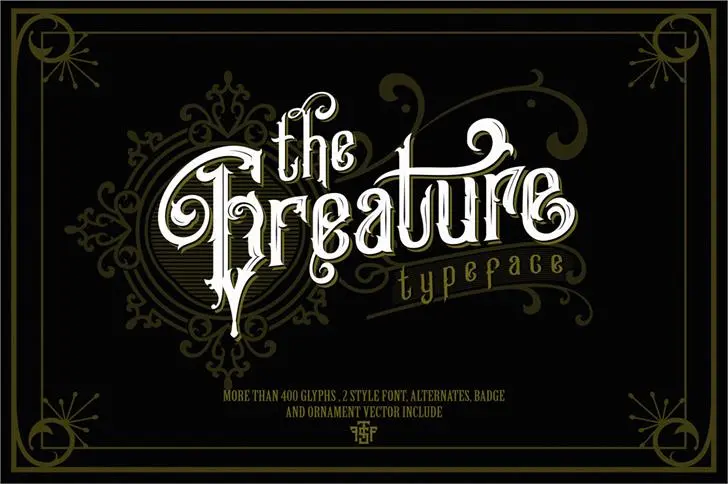
Introduzimos a Greature Font! Desenhada pelo Hamilton, esta fonte apresenta mais de 400 glíptons em duas estilos distintos: Regular e Shine, incluindo conjuntos estilísticos, ligaturas, alternativas contextualizadas e extras (em formato eps e ai) para auxiliar na sua criação. A Greature é inspirada em várias disciplinas artísticas como tatuagem, design tipográfico, pintura de sinais, escrita a lápis e arte vintage, produzindo um resultado visual perfeito para diversos formatos gráficos como etiquetas, panfletos, logotipos, cartão de visita, cabeçalhos, marcação, embalagens e design tipográfico.